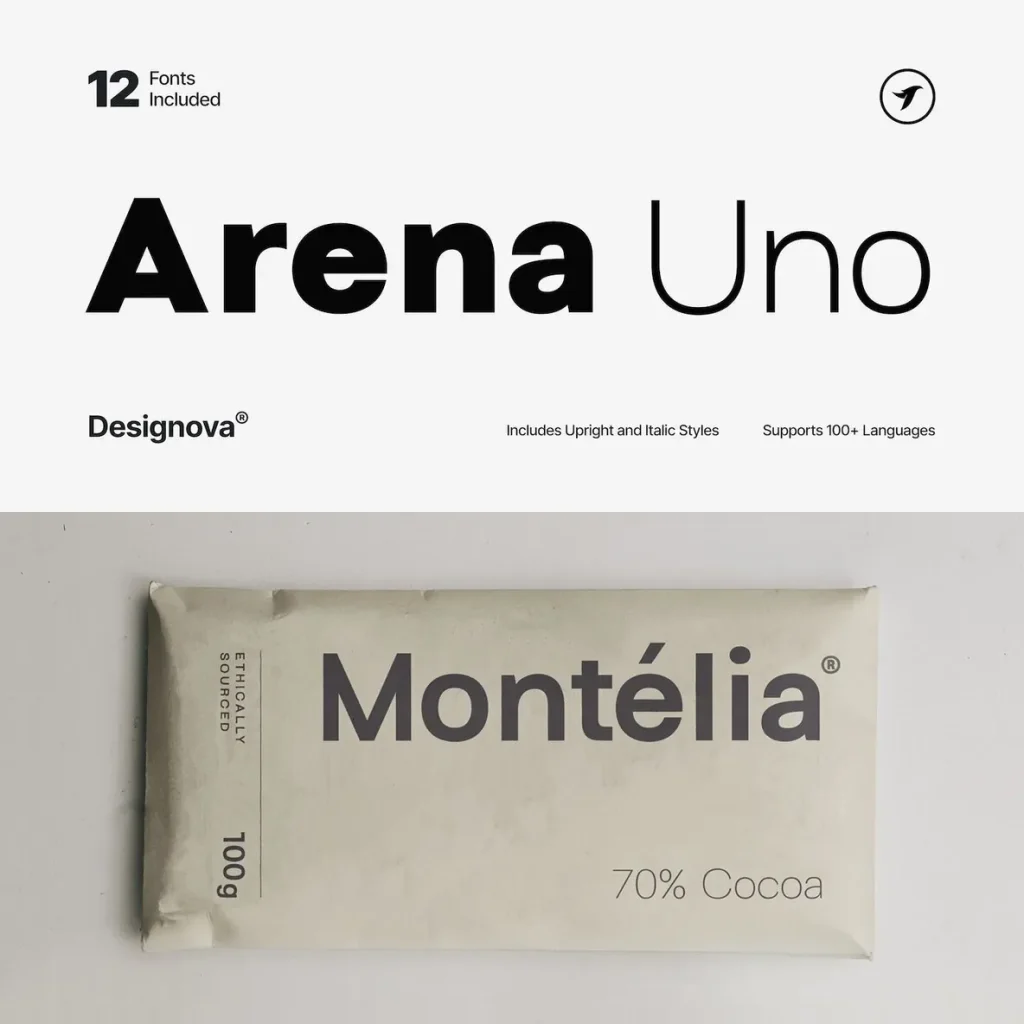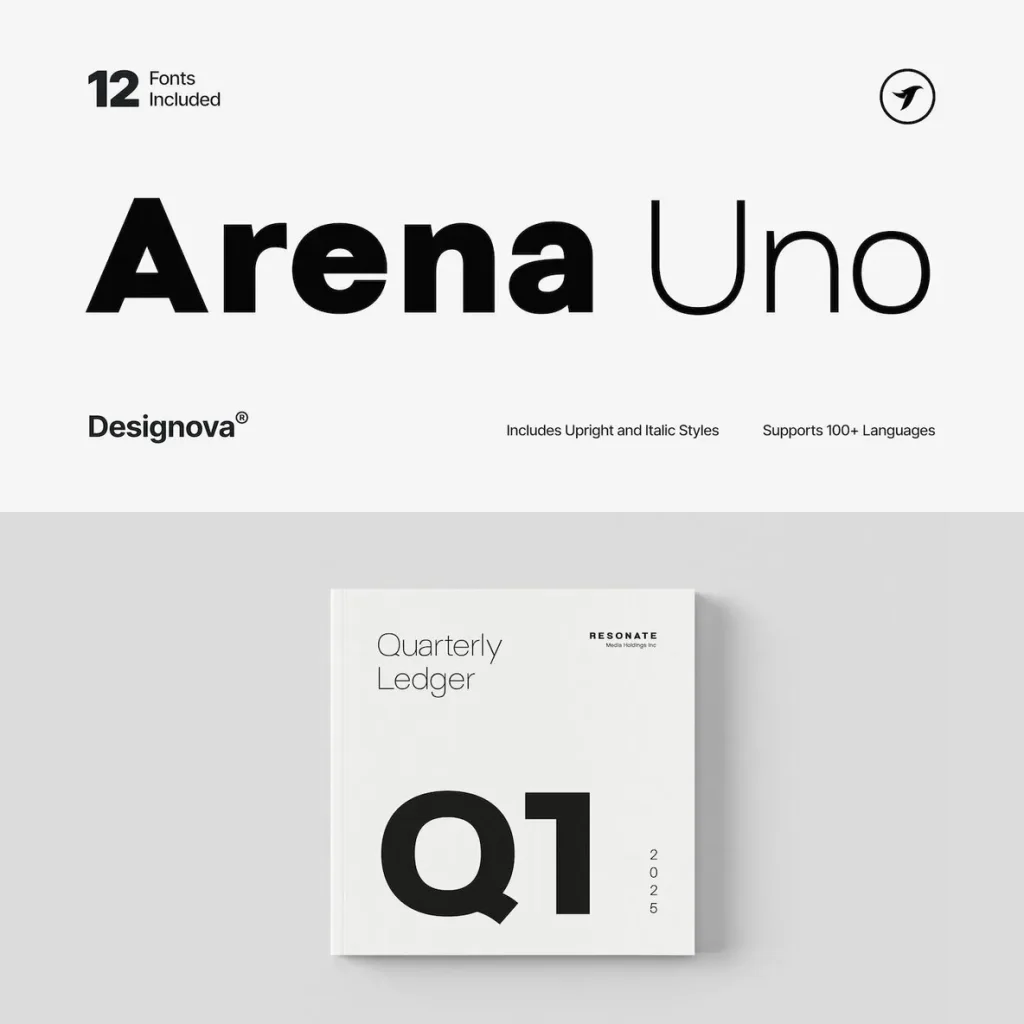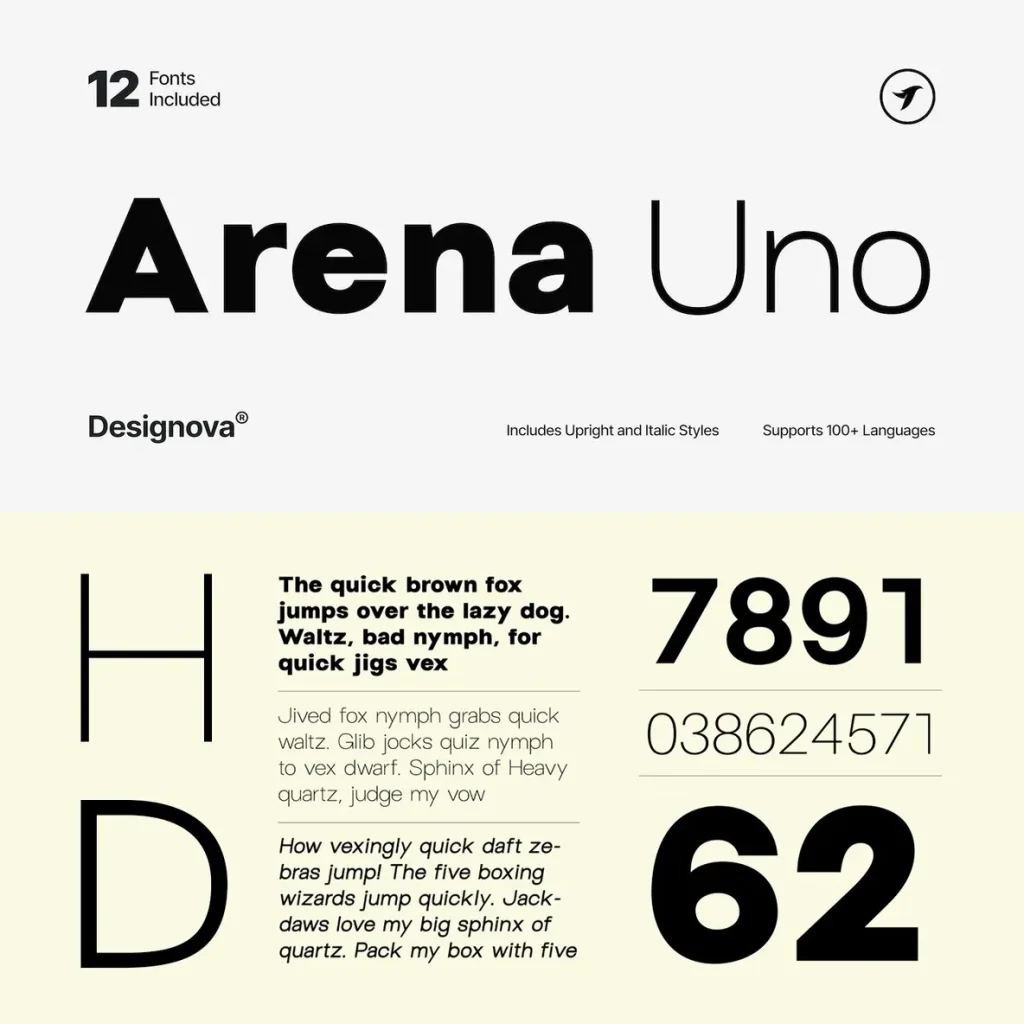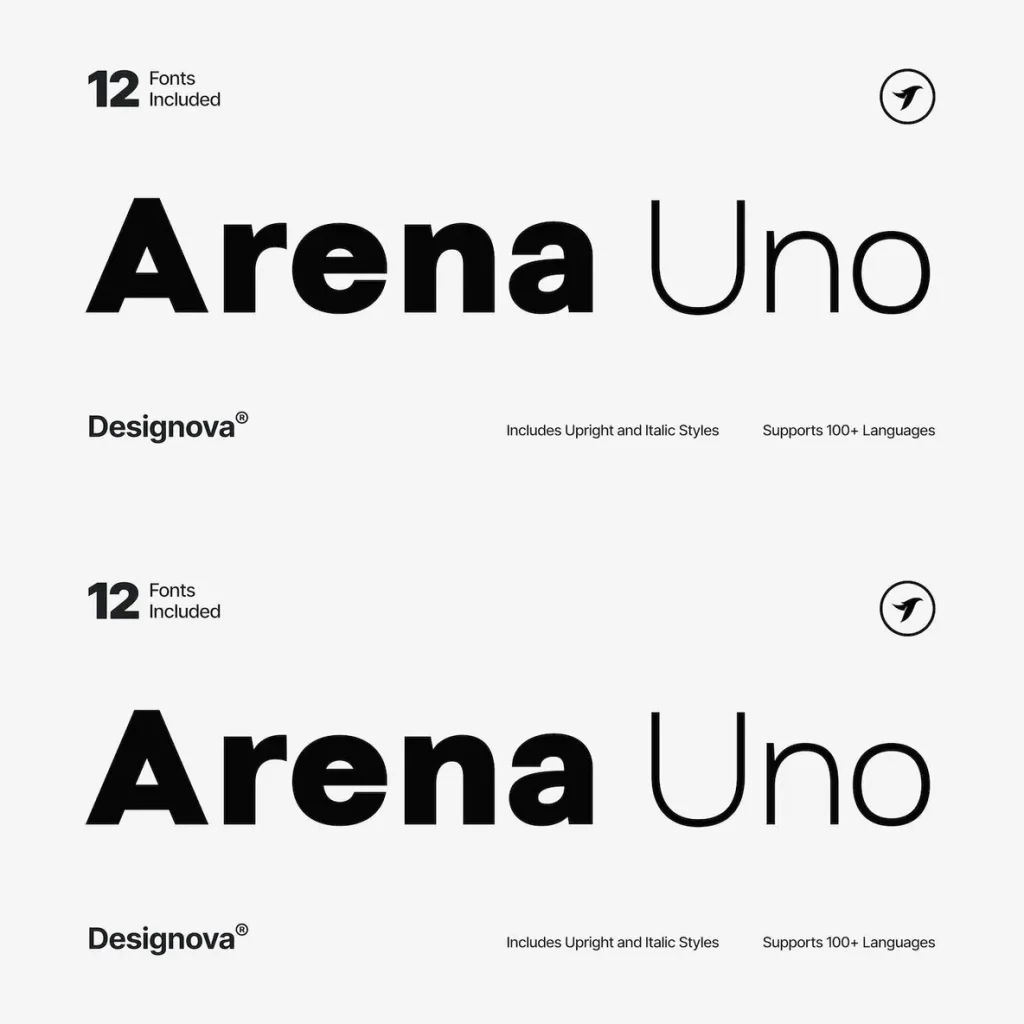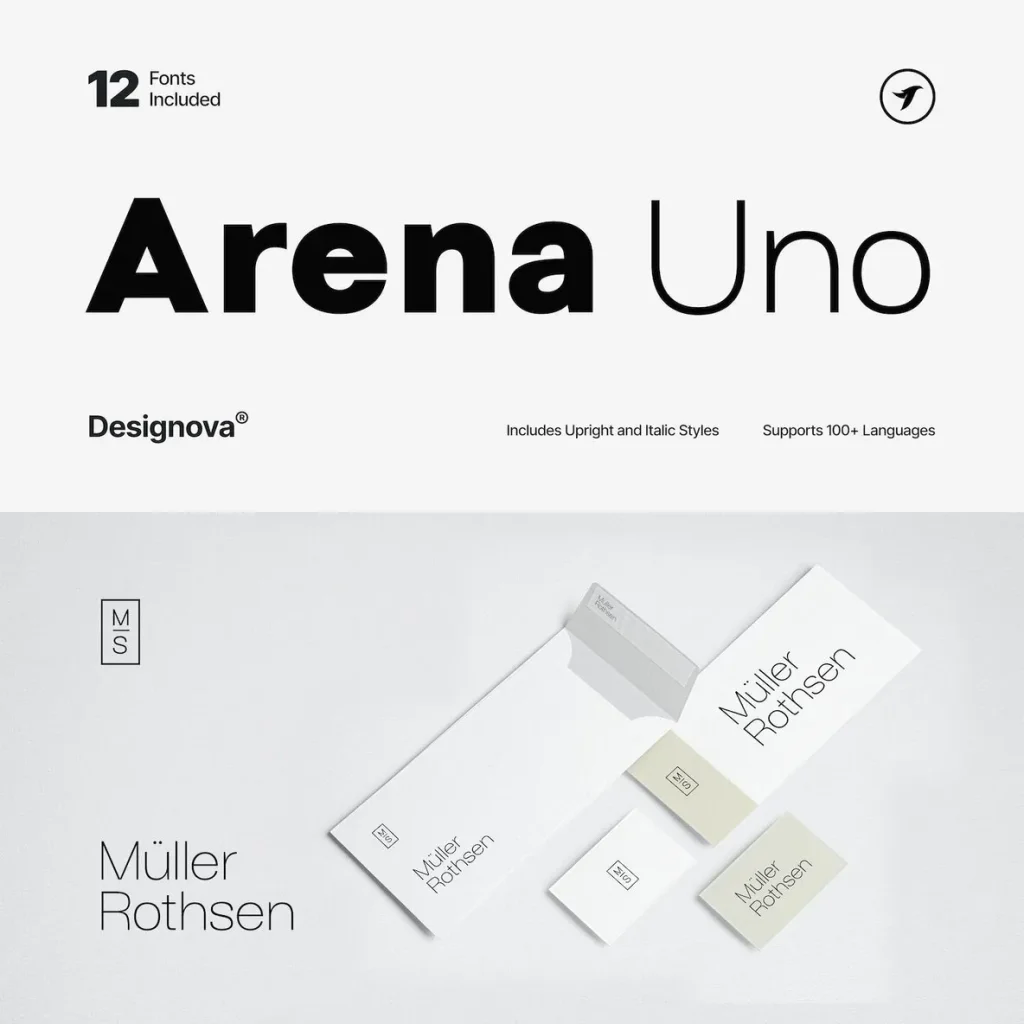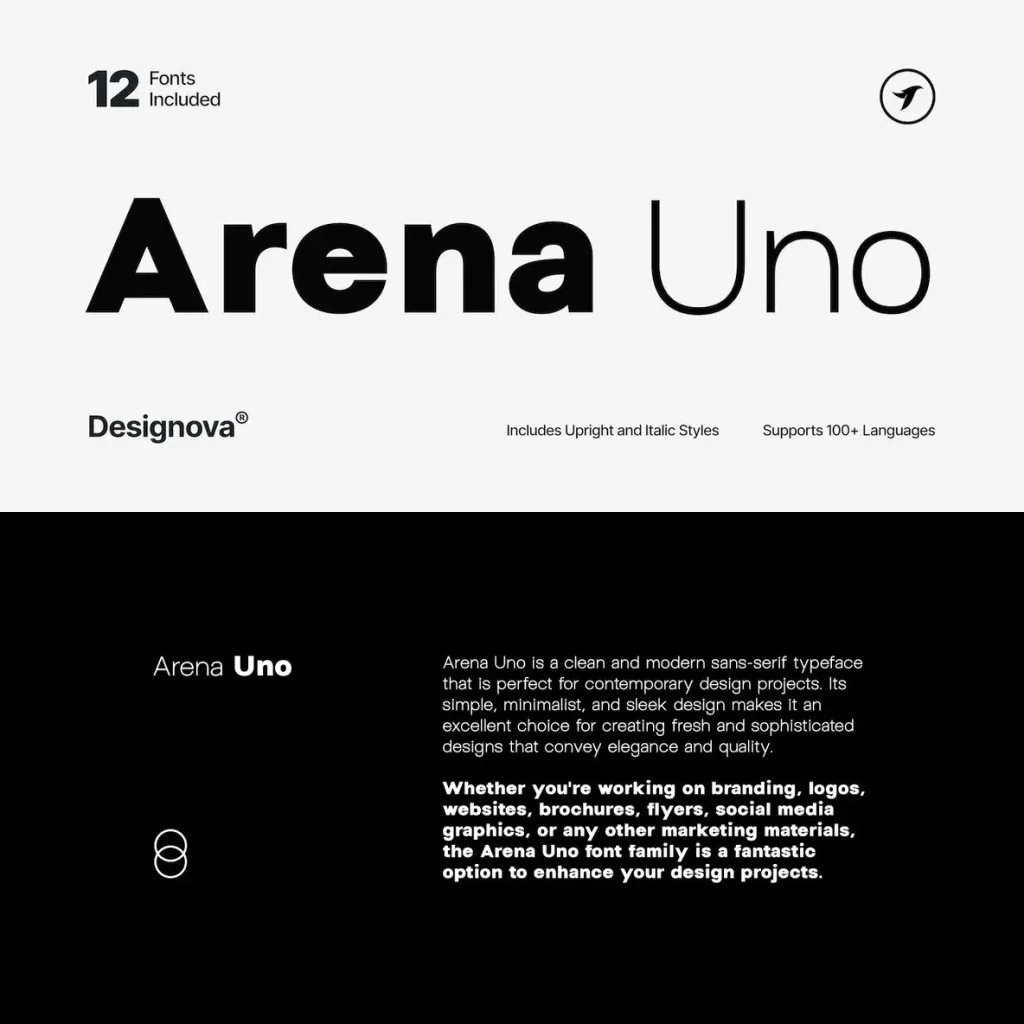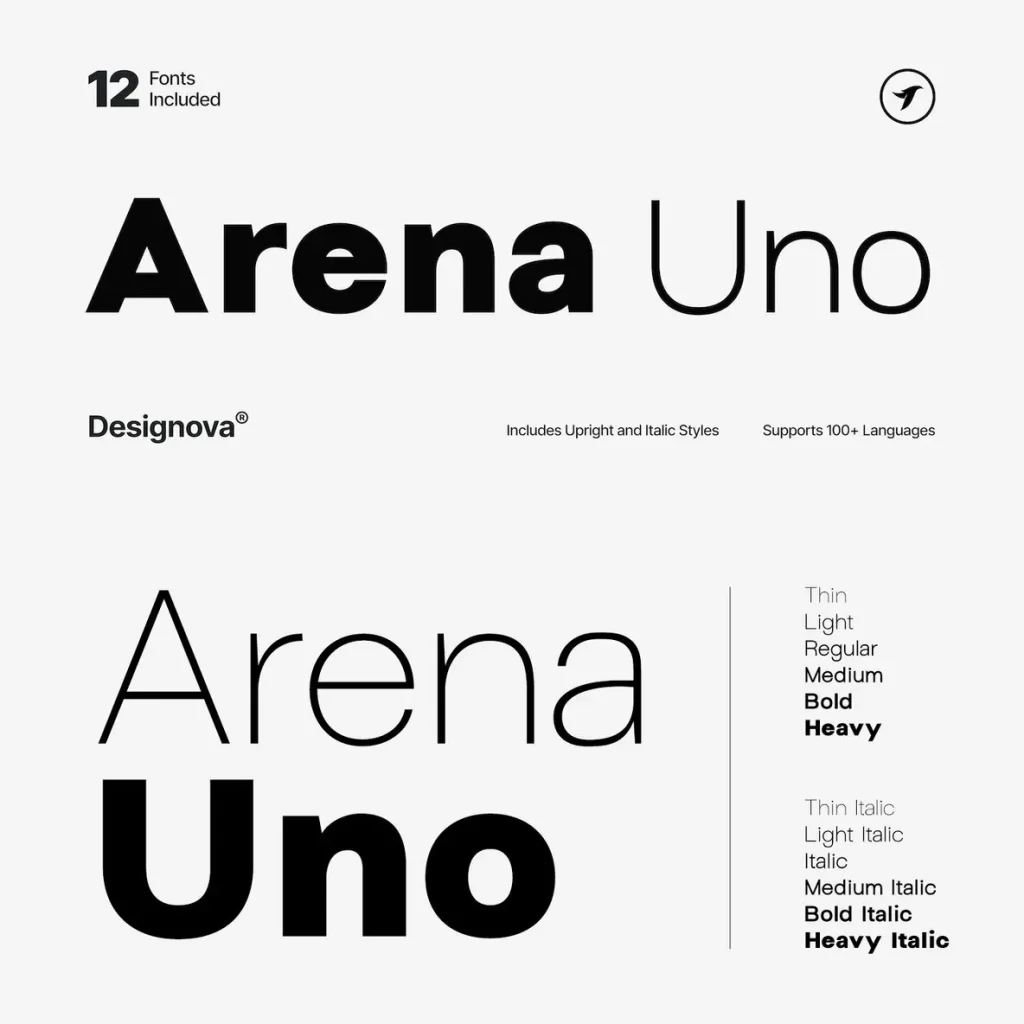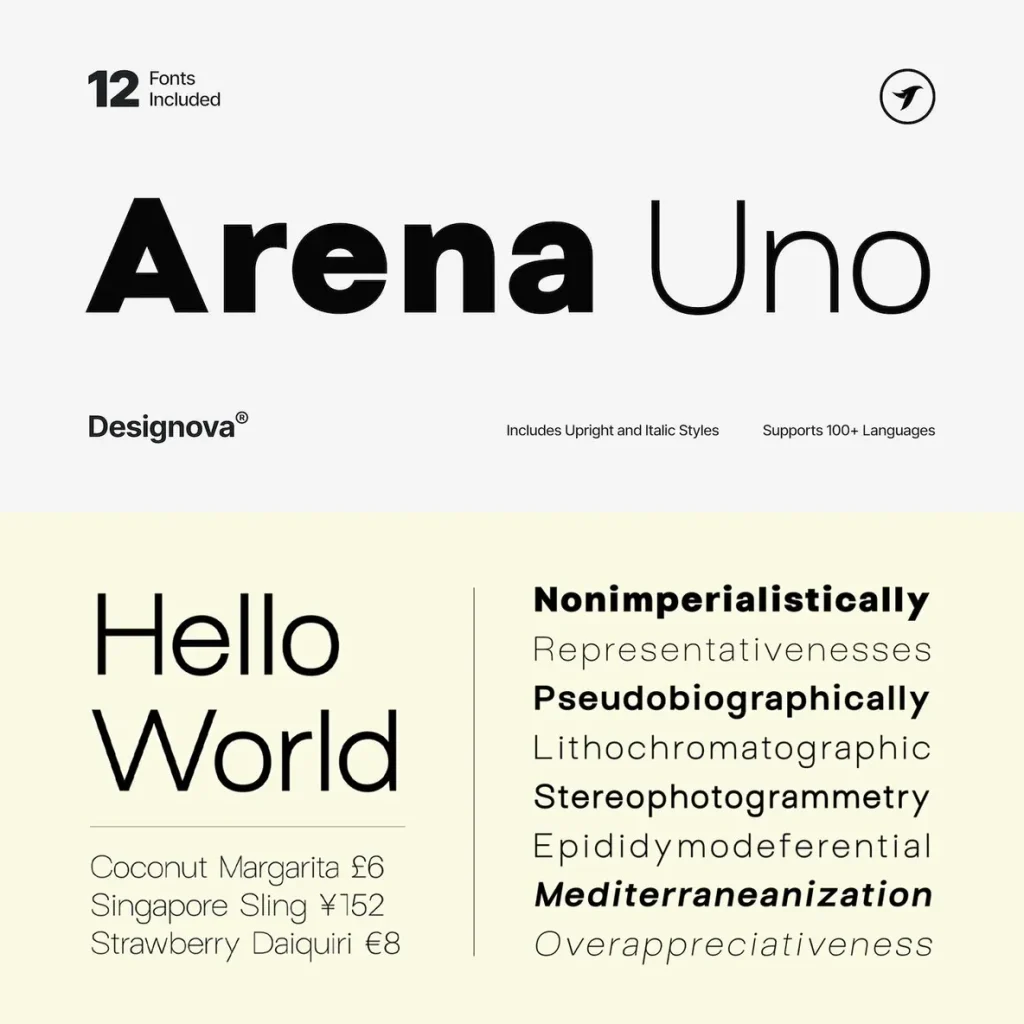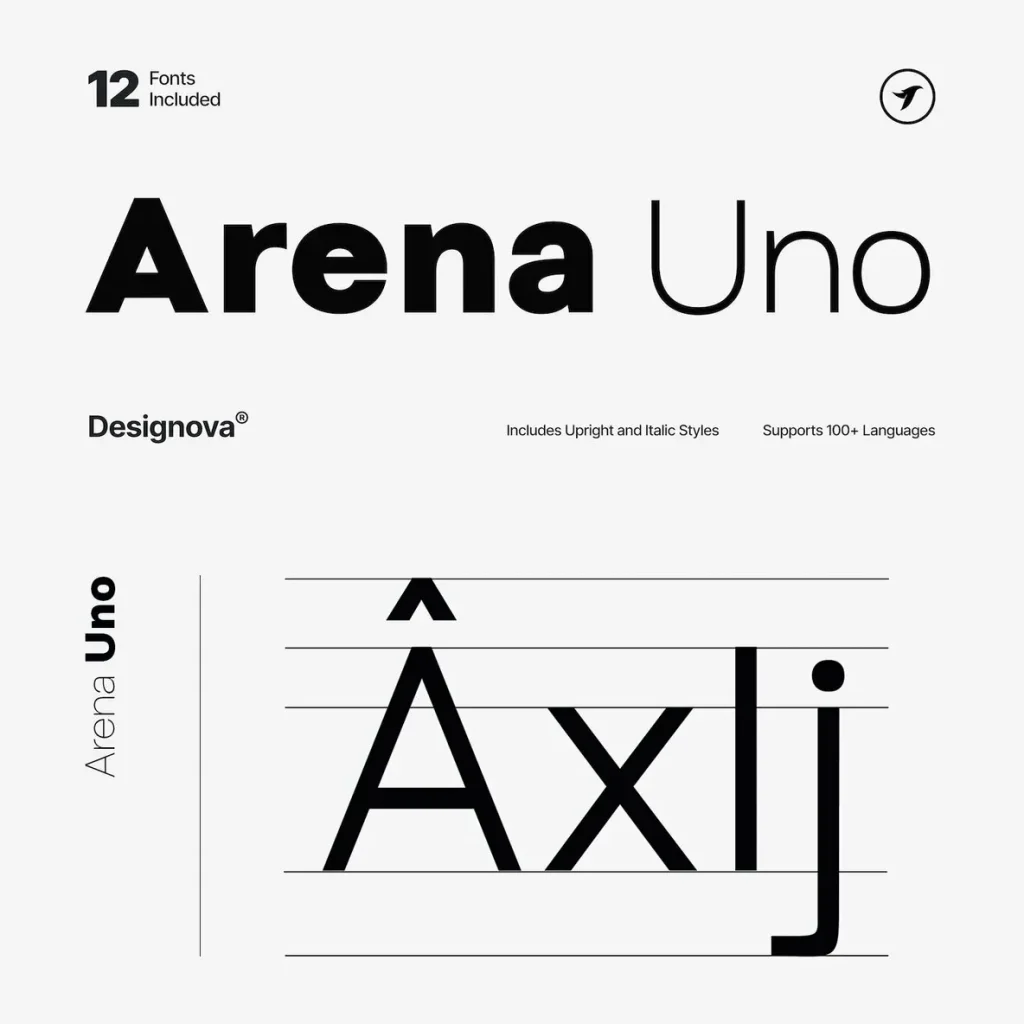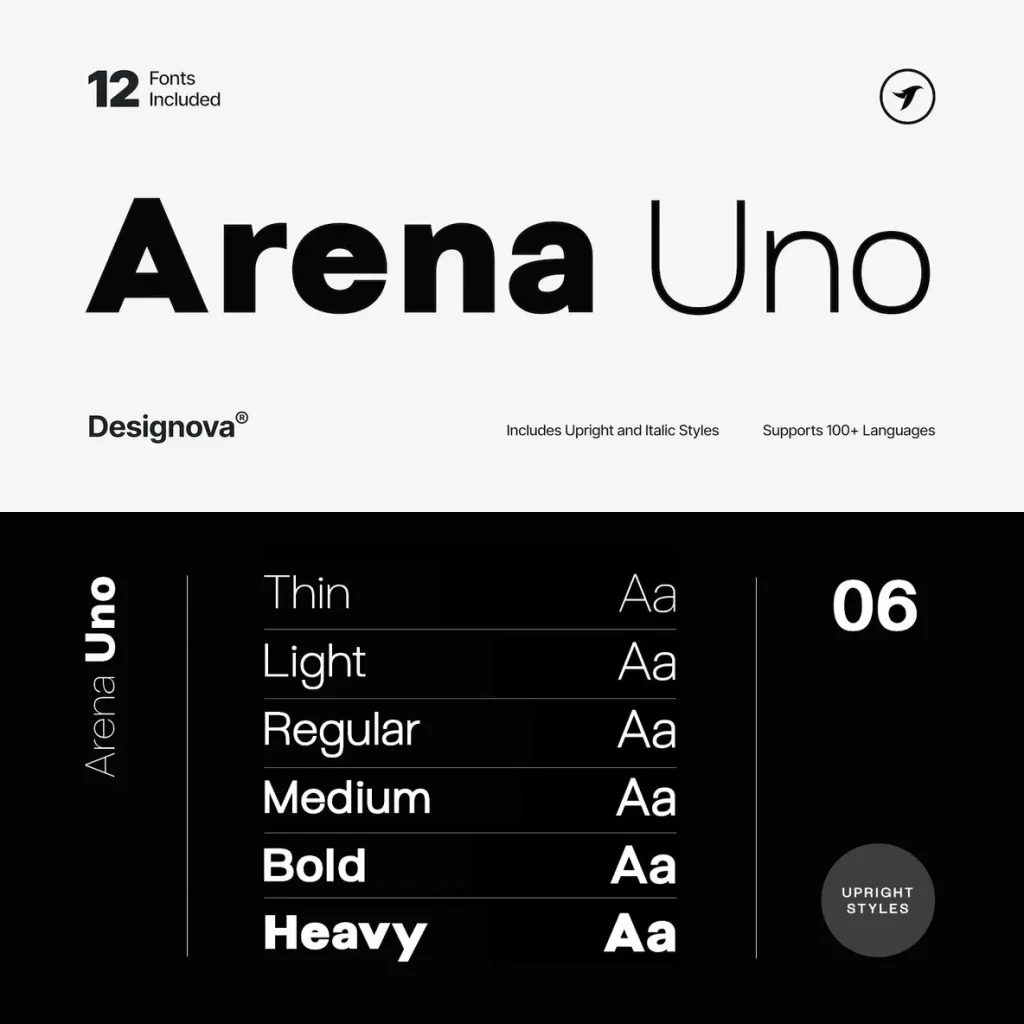
Arena Uno — Klarheit mit System
Arena Uno ist eine moderne serifenlose Schriftfamilie mit klarer Struktur, ausgewogenen Proportionen und einem vielseitigen visuellen Stil. Als Teil der Uno-Schriftfamilien verbindet sie zeitgemäße Einfachheit mit einem fortschrittlichen typografischen System für professionelle Anwendungen.
Ihre raffinierten Buchstabenformen sorgen für Klarheit und Flexibilität in anspruchsvollen Gestaltungskontexten. Arena Uno eignet sich für Branding, Editorial Design, digitale Benutzeroberflächen, Unternehmensmaterialien, Marketinggrafiken und moderne visuelle Kommunikation. Die Familie bietet eine sachliche, präzise typografische Stimme für Projekte, die Struktur, Lesbarkeit und visuelle Kontrolle verlangen.